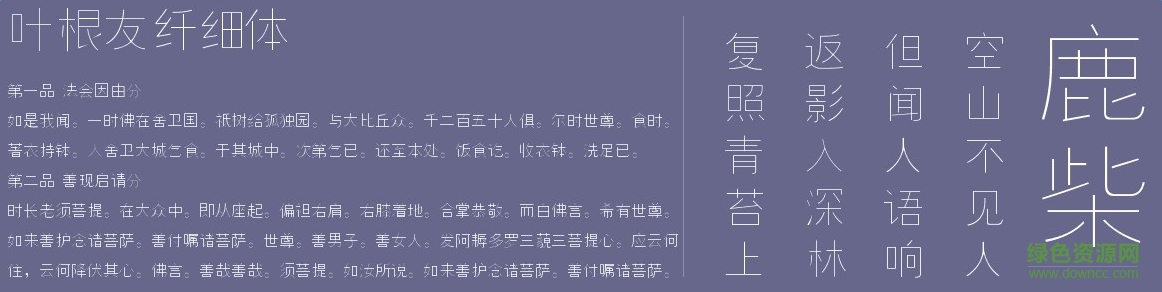
叶根友纤细体是一款由知名书法家叶根友创造的字体,比划圆润,适用于广告、艺术设计,海报设计等方面,有需要的朋友们不要错过了。欢迎大家来绿色资源网踊跃下载哦!
叶根友纤细体,一款经典的细体风格的字体,所有叶根友系列字体中笔画最细的字体,适合内文排版,手机系统,内嵌程序等应用。
叶根友纤细体,用途广泛,是叶根友先生的印刷字体,字体看起来柔美,纤细,如同柳枝轻抚书页,看起来很舒心。各位字体收藏者可以来看看。